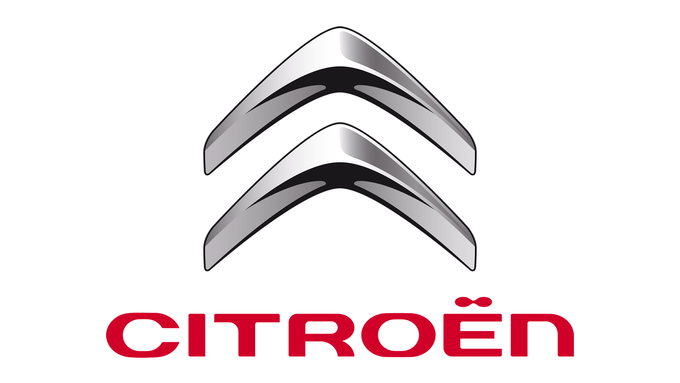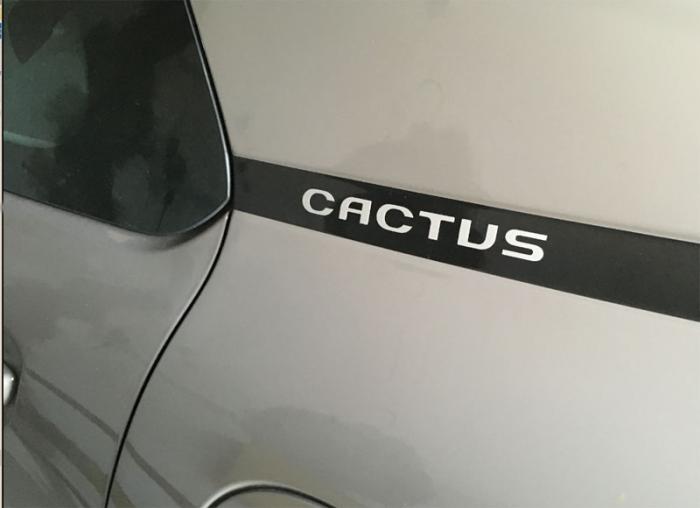
[Mitglied Cava…] Geschrieben März 16, 2016 Teilen Geschrieben März 16, 2016 Hallo erstmal Ich möchte auf meinem Citroen Cactus den Originalschriftzug "CACTUS" als Aufkleber von meinen Kollegen herstellen lassen. Leider finde ich weder eine vernünftige Vorlage noch den Schriftfont. Vielleicht könntet ihr mir weiterhelfen. Citroen rückt diesen Font leider nicht raus. Grüße Cavatelli Link zu diesem Kommentar
[Mitglied catf…] Geschrieben März 16, 2016 Teilen Geschrieben März 16, 2016 Da wird es, außer diesen 5 Buchstaben, die wohl ein grafiker gezeichnet hat, kaum einen Font geben Link zu diesem Kommentar
[Mitglied 91d0…] Geschrieben März 16, 2016 Teilen Geschrieben März 16, 2016 Der leitet sich vom Citroën-Schritzug ab … Könnte man mi wenigen Handgriffen aus diesem generieren, wenn man den Citroën-Schriftzug vektorbasiert hätte … Link zu diesem Kommentar
[Mitglied Cava…] Geschrieben März 17, 2016 Themen-Ersteller Teilen Geschrieben März 17, 2016 So...das ist nun das Endergebnis. Bei Citroen hätte ein Original-Aufkleber 20 Euro gekostet. Mein Arbeitskollege hat es mir einfach aus Freundschaft geschnitten. Nochmals herzlichen Dank für die tolle Vorlage. 1 Link zu diesem Kommentar